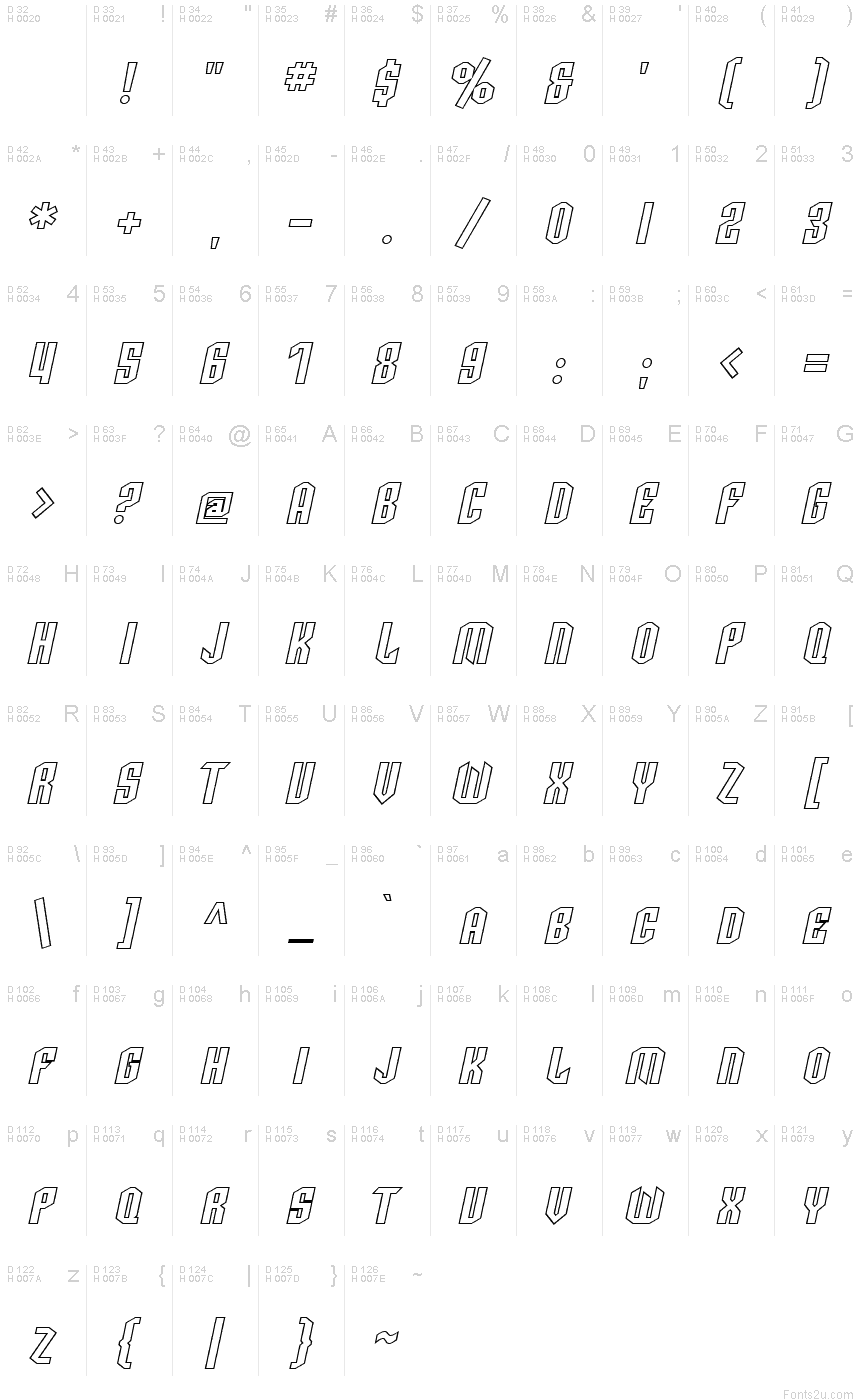
يُعد SF Archery من ShyFoundry خطاً تقنياً (techno) مجانياً يعتمد على الحروف الكبيرة (caps)، ويتميز بطابعه الحاد والسريع. تميل الحروف إلى الأمام بأشكال كتلية وزوايا حادة، مع دمج زوايا مقصوصة وفتحات داخلية طويلة تمنح الخط طابعاً هندسياً ورياضياً، مع لمسة مستوحاة من ألعاب الأركيد.
إنه مثالي لعناوين الملصقات، وتصميم العلامات التجارية للرياضات الإلكترونية (esports)، وعناوين الألعاب، ورسومات الفعاليات الرياضية، والأغلفة التي تتطلب شعاراً مضغوطاً يوحي بالحركة دون فقدان بنيته القوية. وبما أنه خط مجاني، فهو مناسب أيضاً للشعارات (logos)، والرموز المدمجة، والنصوص القصيرة على اللافتات، حيث تمنح التشكيلات المسننة المتكررة للنصوص القصيرة مظهراً محكماً ومخصصاً.
رموز خط SF Archery Black SC Outline Oblique — الأساسية لاتينية، الصفحة 1